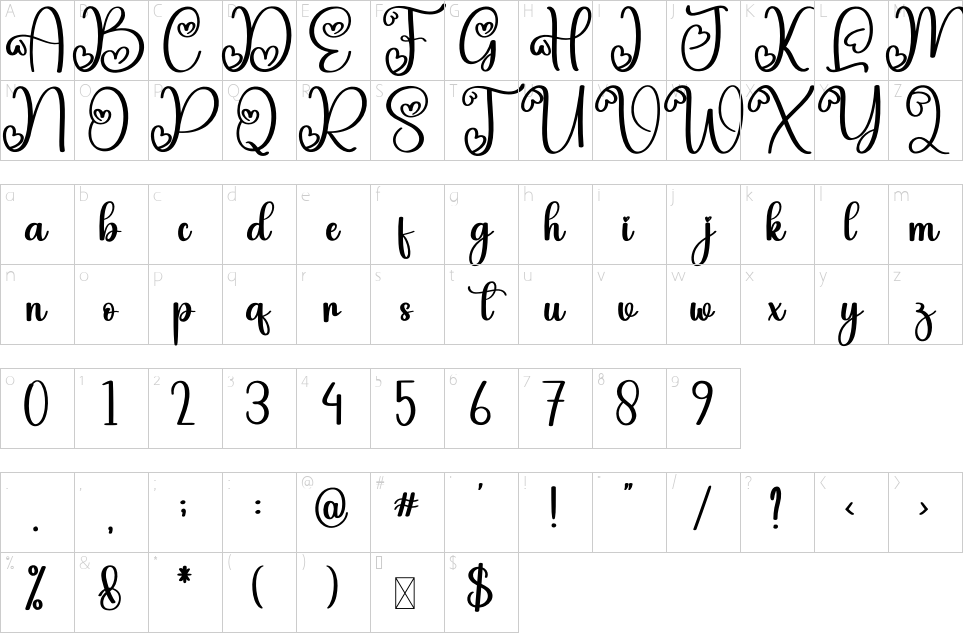
A Sand Beach Font é uma delícia para quem busca fontes com um toque de tranquilidade e conforto. Essa elegante fonte foi projetada por um designer anônimo e já foi baixada 1.541 vezes. Ela combina bem em sites de surf, blogs de viagens ou até mesmo sites de design gráfico, adicionando um toque tropical a qualquer projeto. Com linhas suaves e um tamanho que se adapta bem a qualquer fonte de texto, é uma ótima opção para quem busca um estilo natural e descontraído. Seja para um post sobre uma viagem a uma praia deslumbrante ou para um projeto de design de escritório, a Sand Beach Font é uma escolha perfeita. Descubra a tranquilidade da praia em cada caractere.